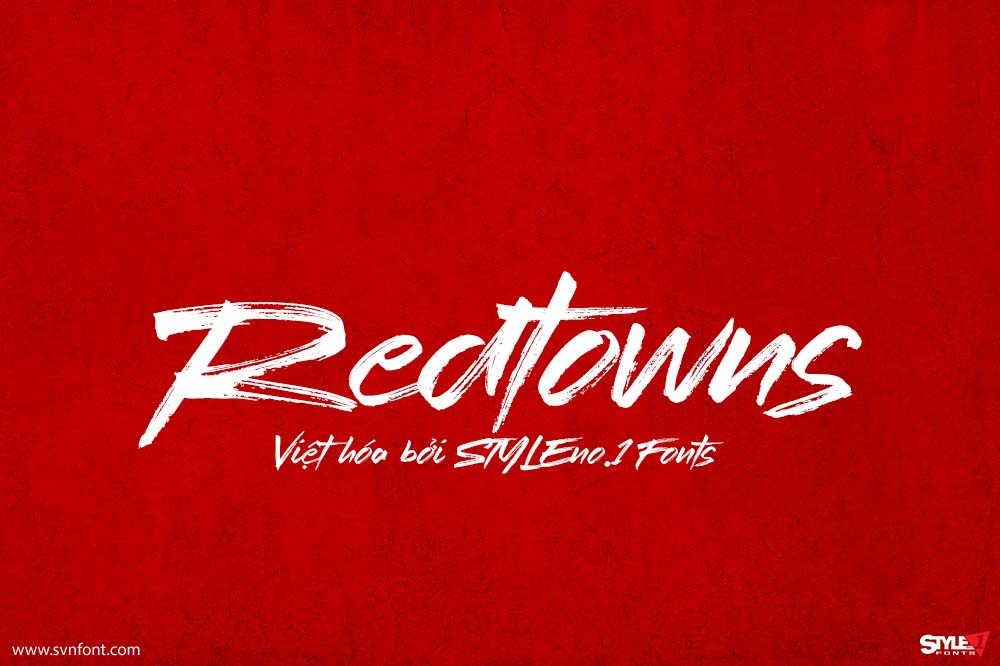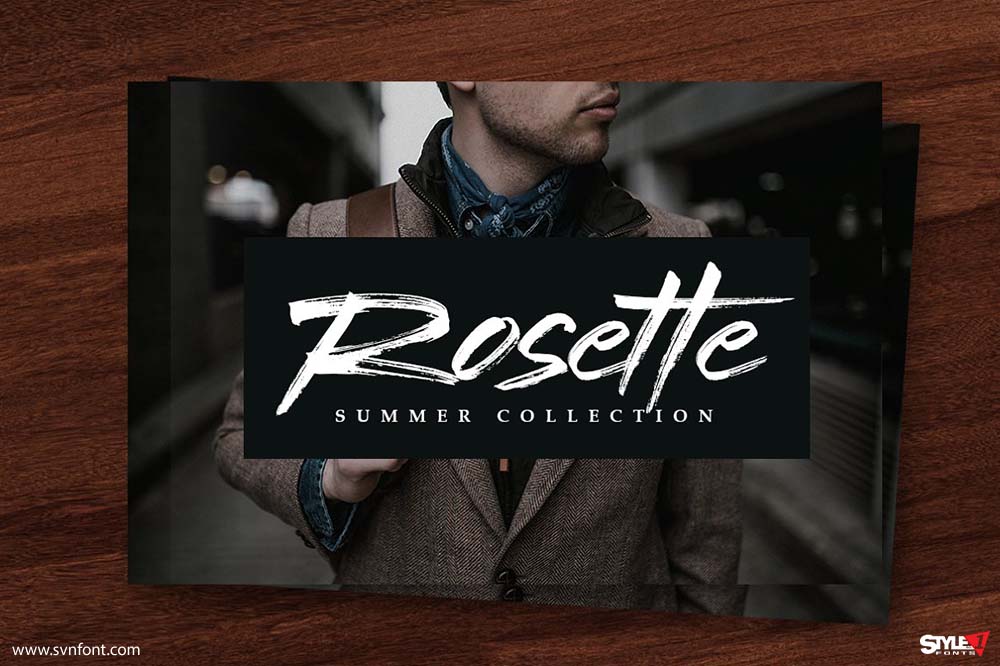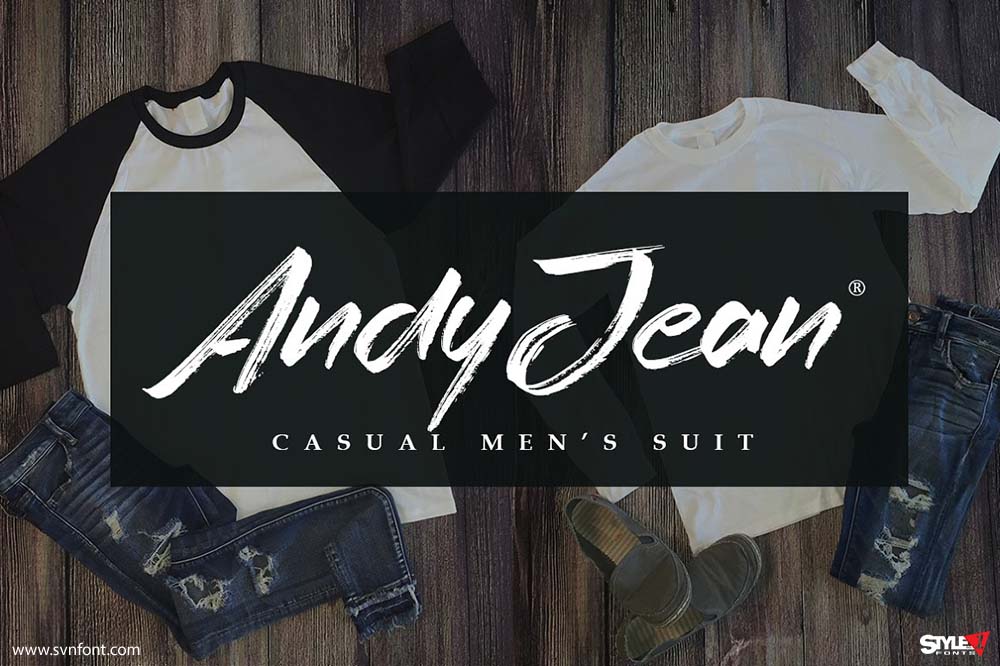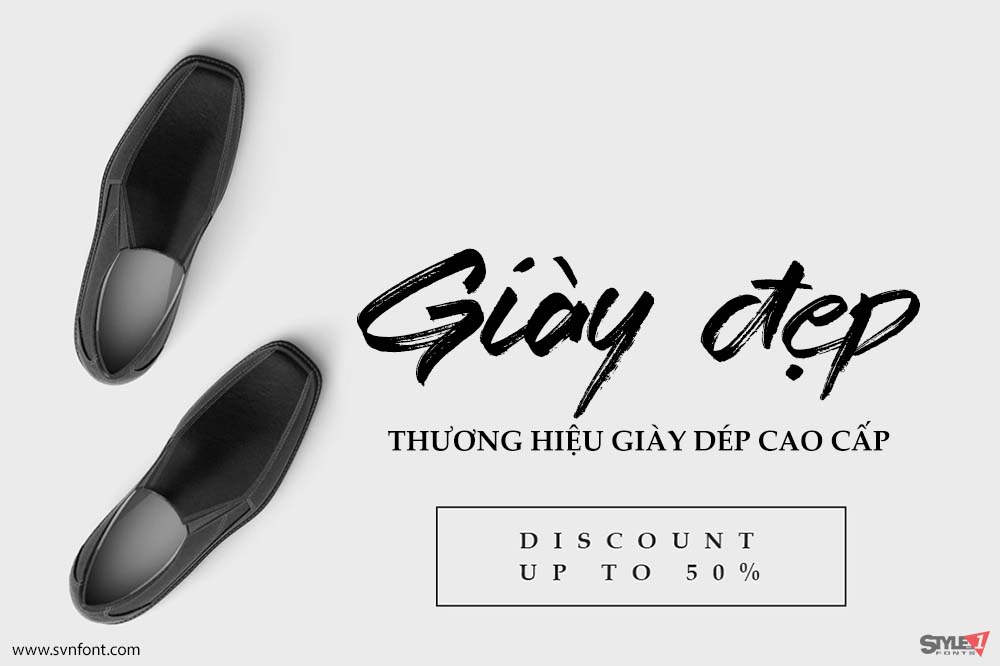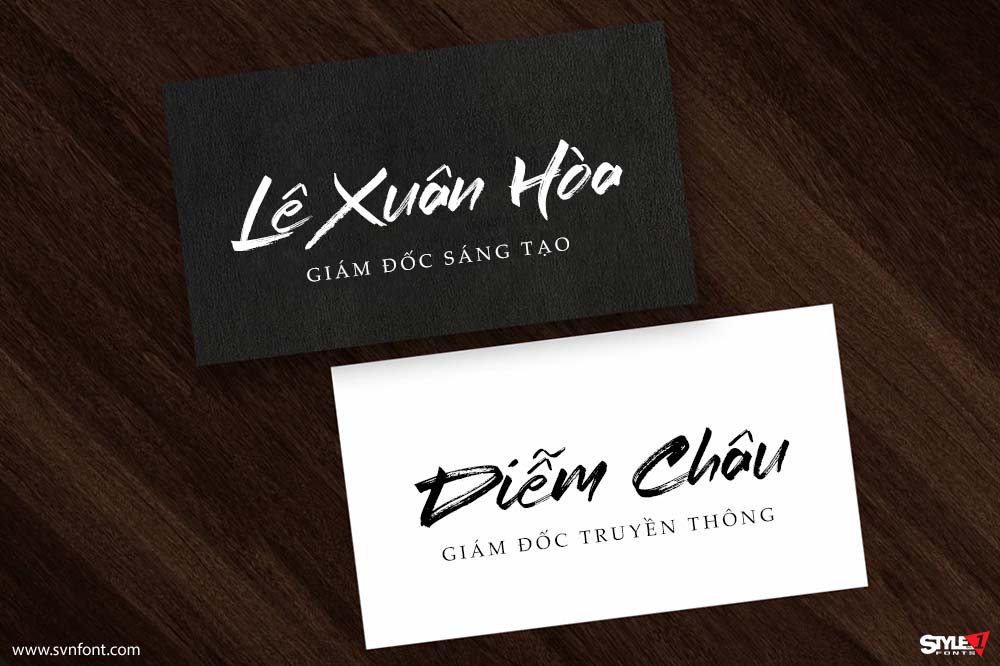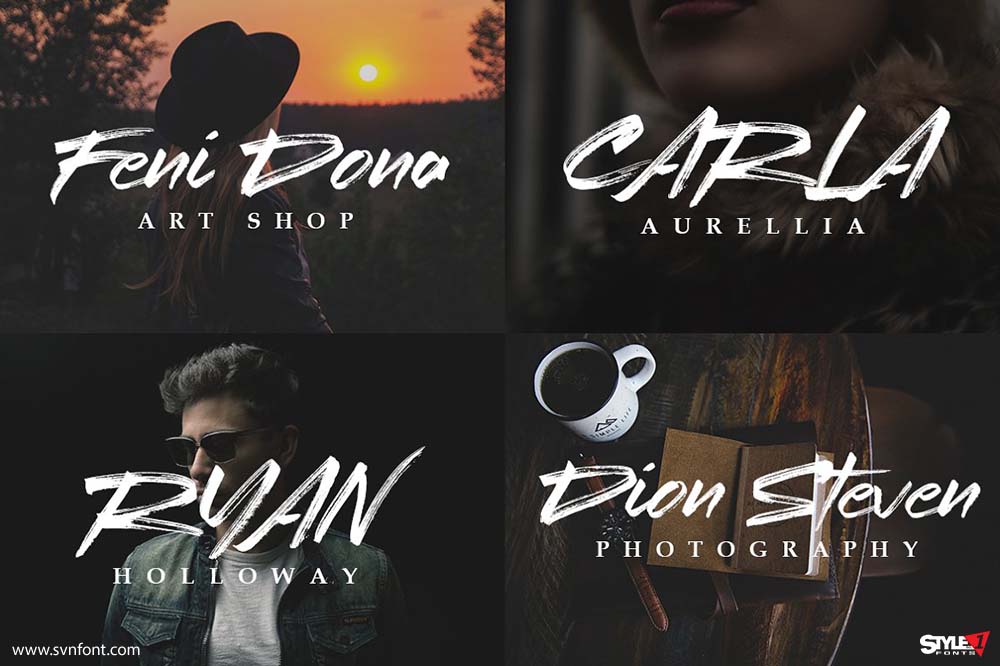
Font Việt Hóa SVN- Redtowns Thiết Kế Từ Bút Lông Tuyệt Đẹp
Redtowns - một brush font được thiết kế từ bút lông và giấy. Font thích hợp tuyệt vời cho các dự án thiết kế như quần áo, chữ ký, hình mờ, ảnh, áp phích, thương hiệu…
Nhà thiết kế: Lettersiro
Việt hóa: STYLEno.1 Fonts